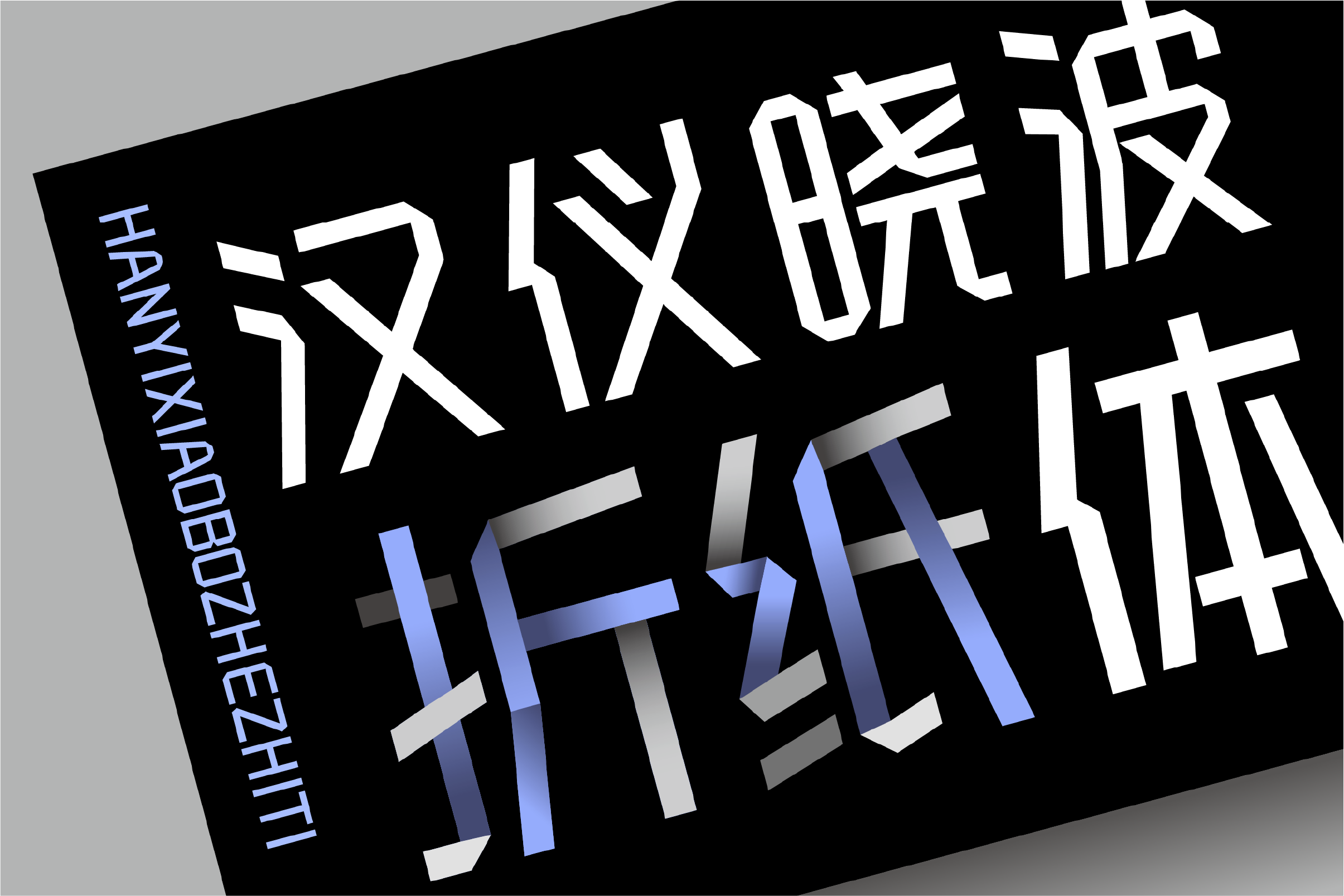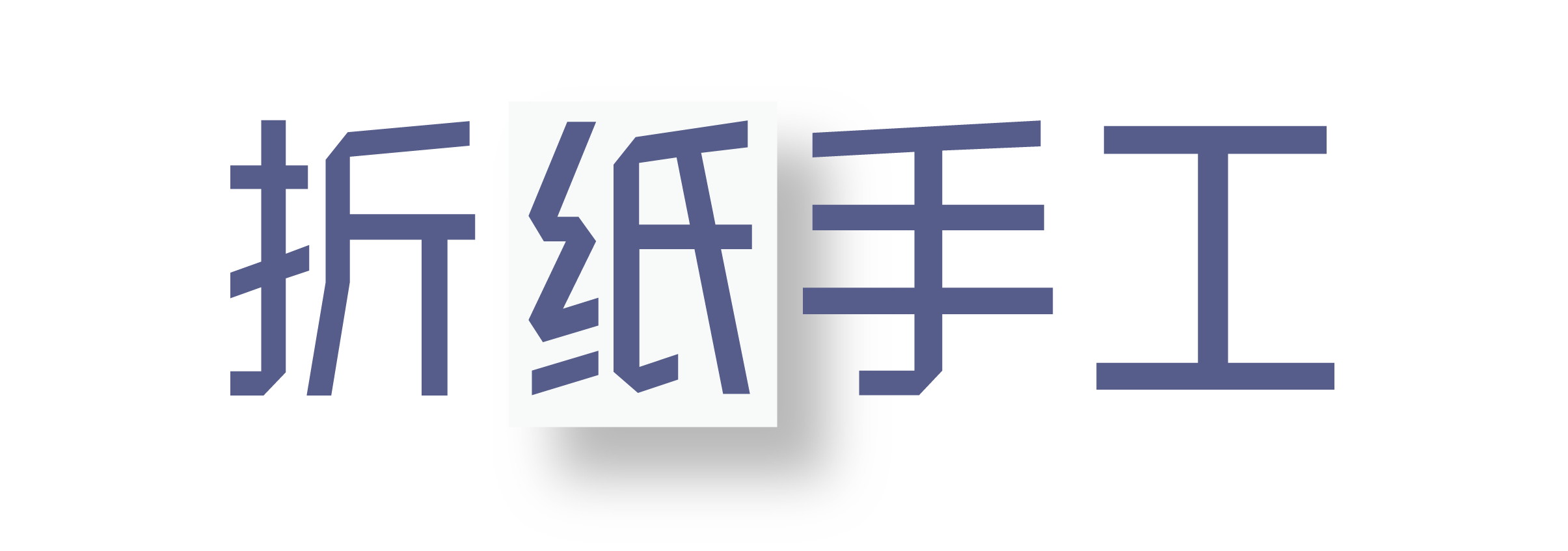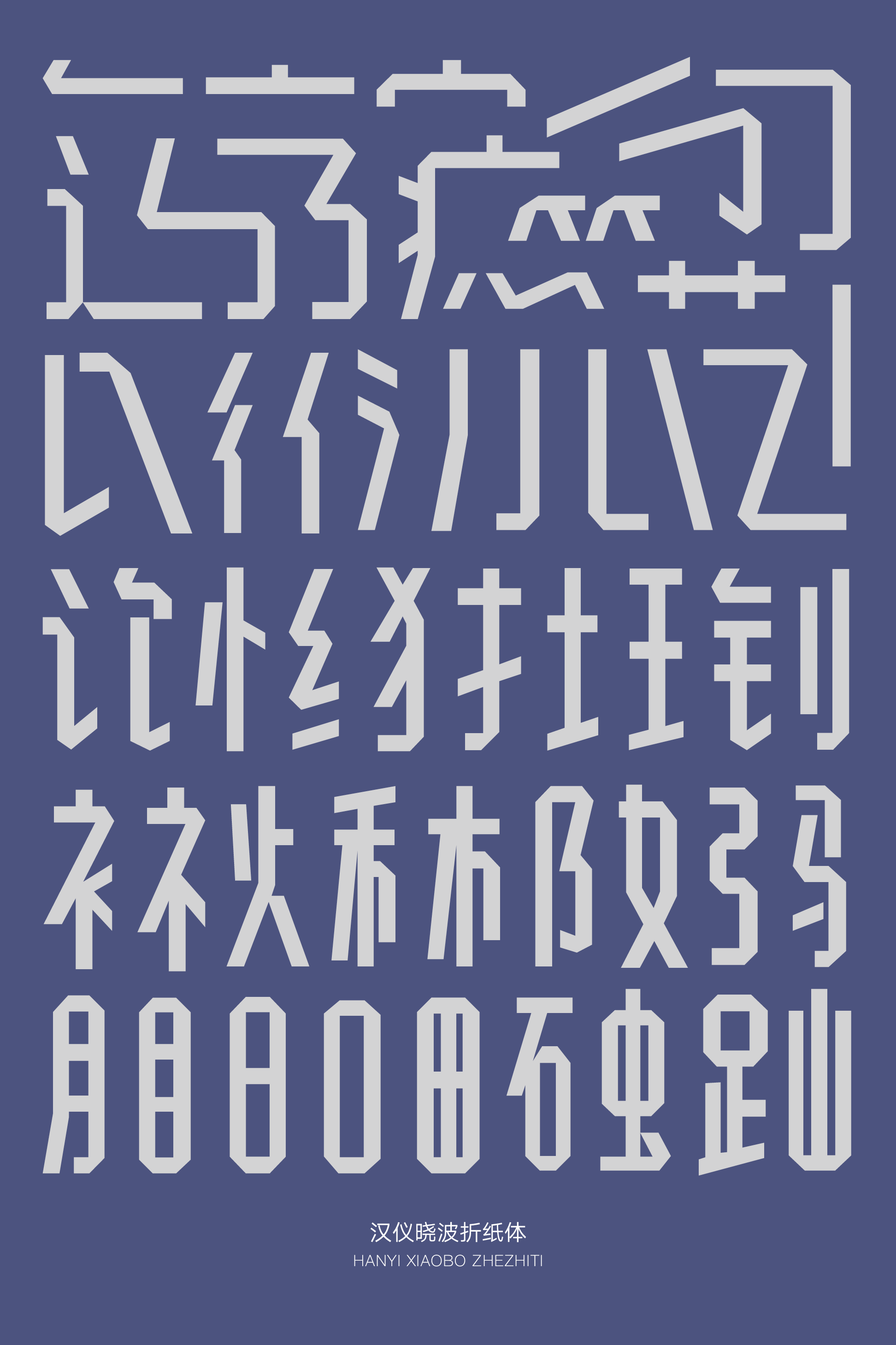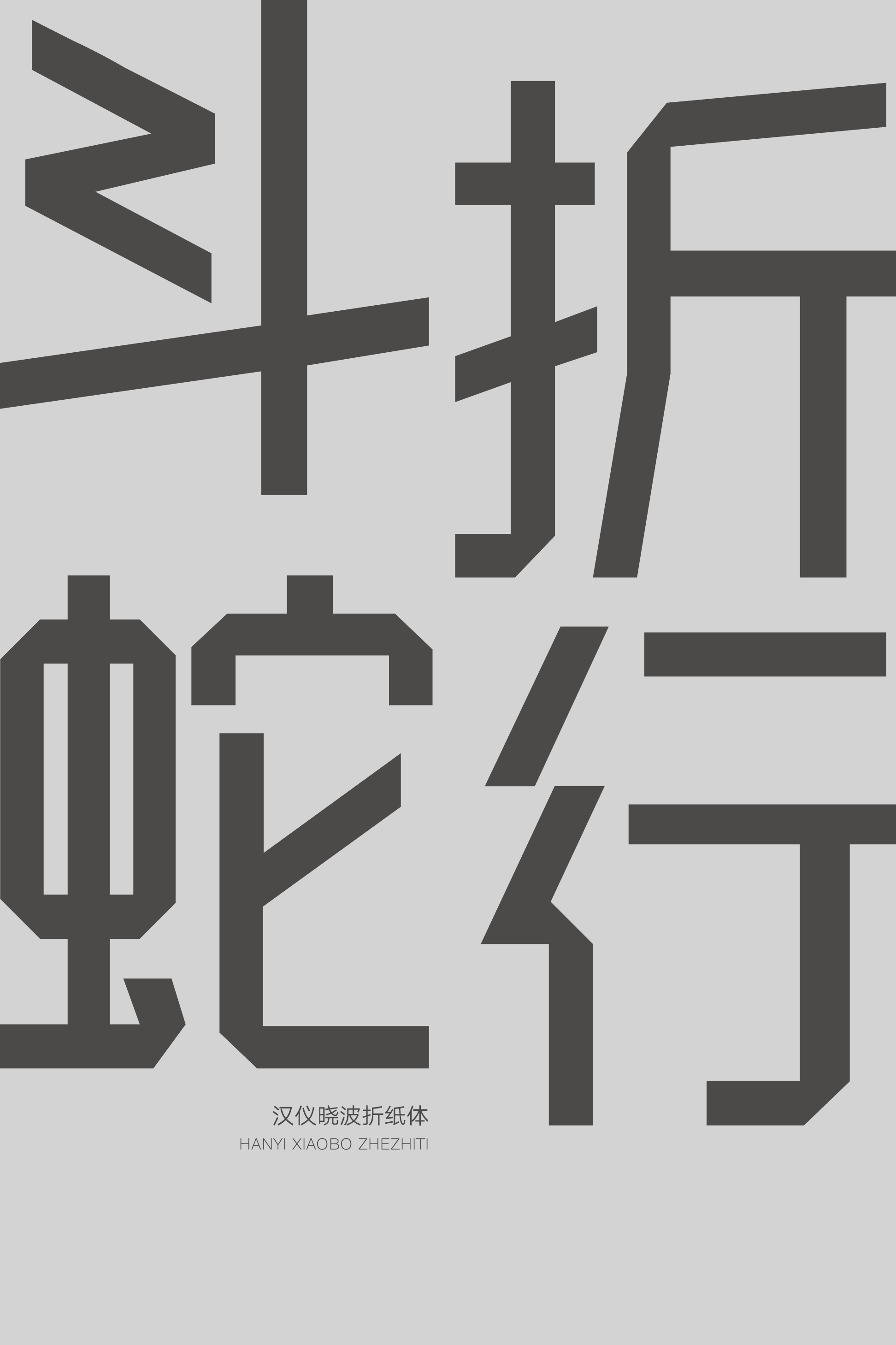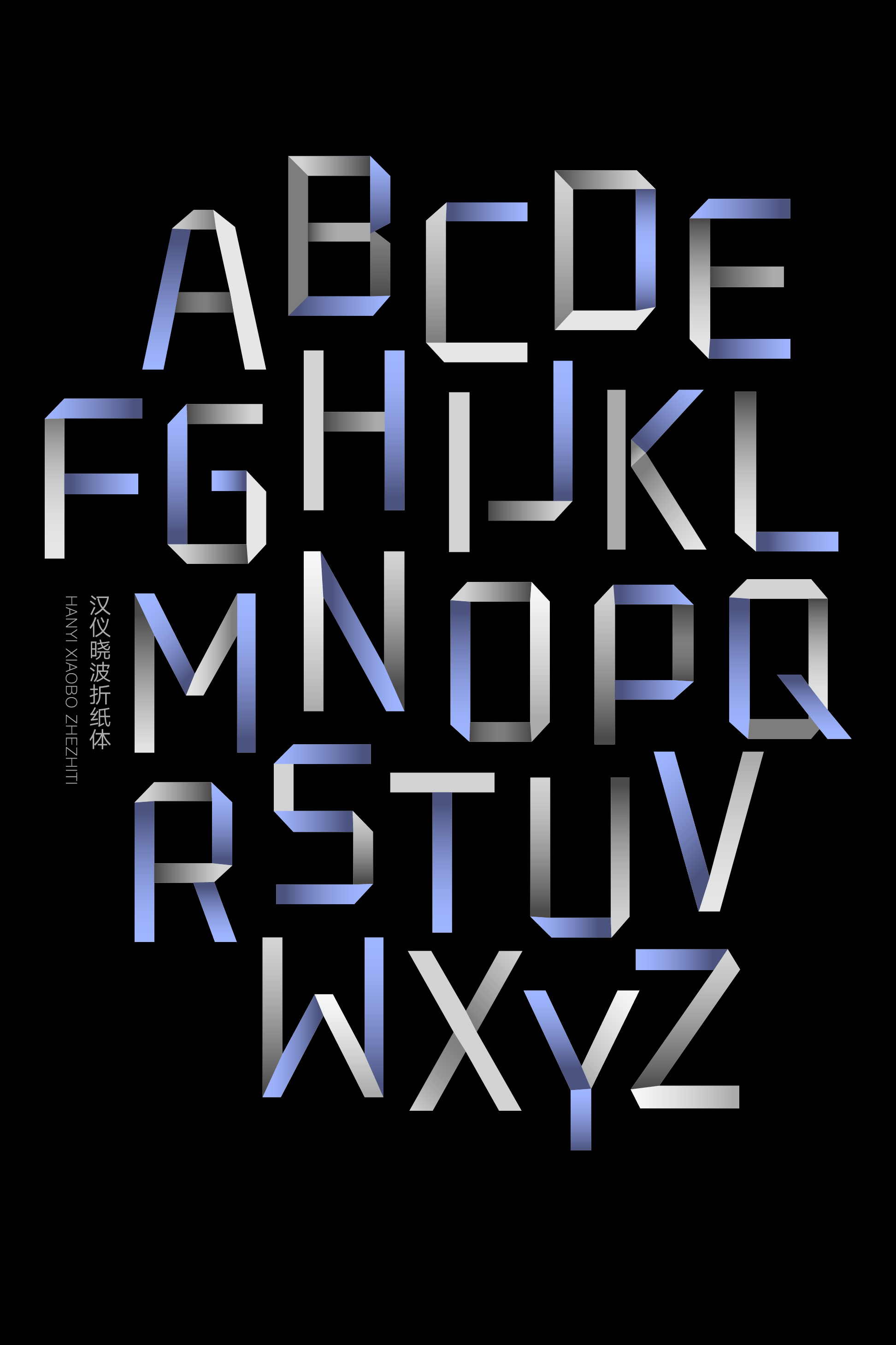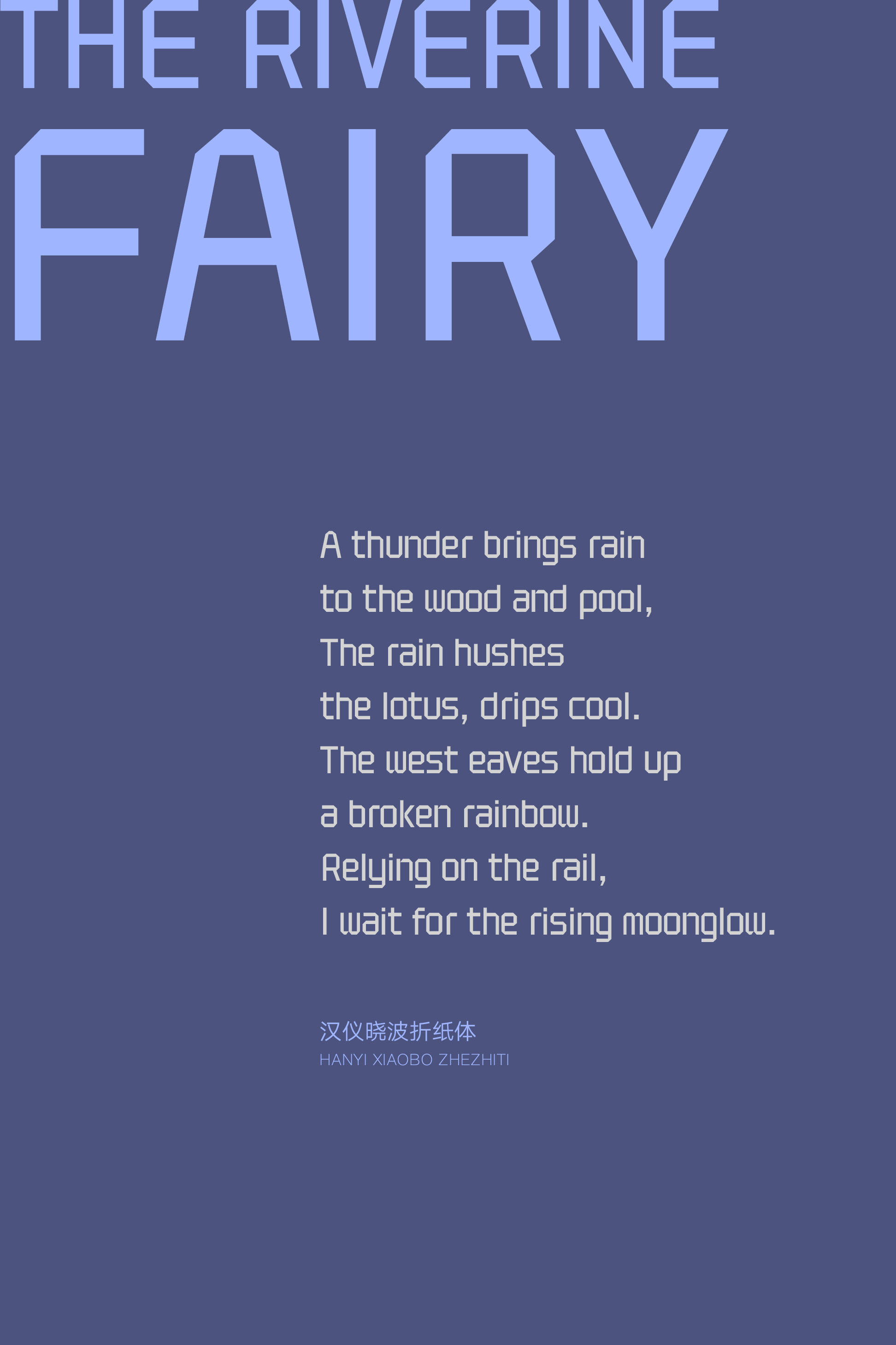
汉仪晓波折纸体
汉仪晓波折纸体,将折纸的几何趣味融入字体设计,带来轻松愉快的视觉体验。轻量而窄长的造型如同纸张,巧妙折叠出笔画的转折,鲜活生动。这款字体适合用于儿童玩具绘本、益智教育、影视动画等使用场景,细节满分,简约而不简单。
字形偏窄长,如纸张般轻量。
纸张折叠变成笔画的转折和连带,巧妙灵活。
西文部分保留窄长的造型和折纸的设计细节,中西文搭配带来手工趣味